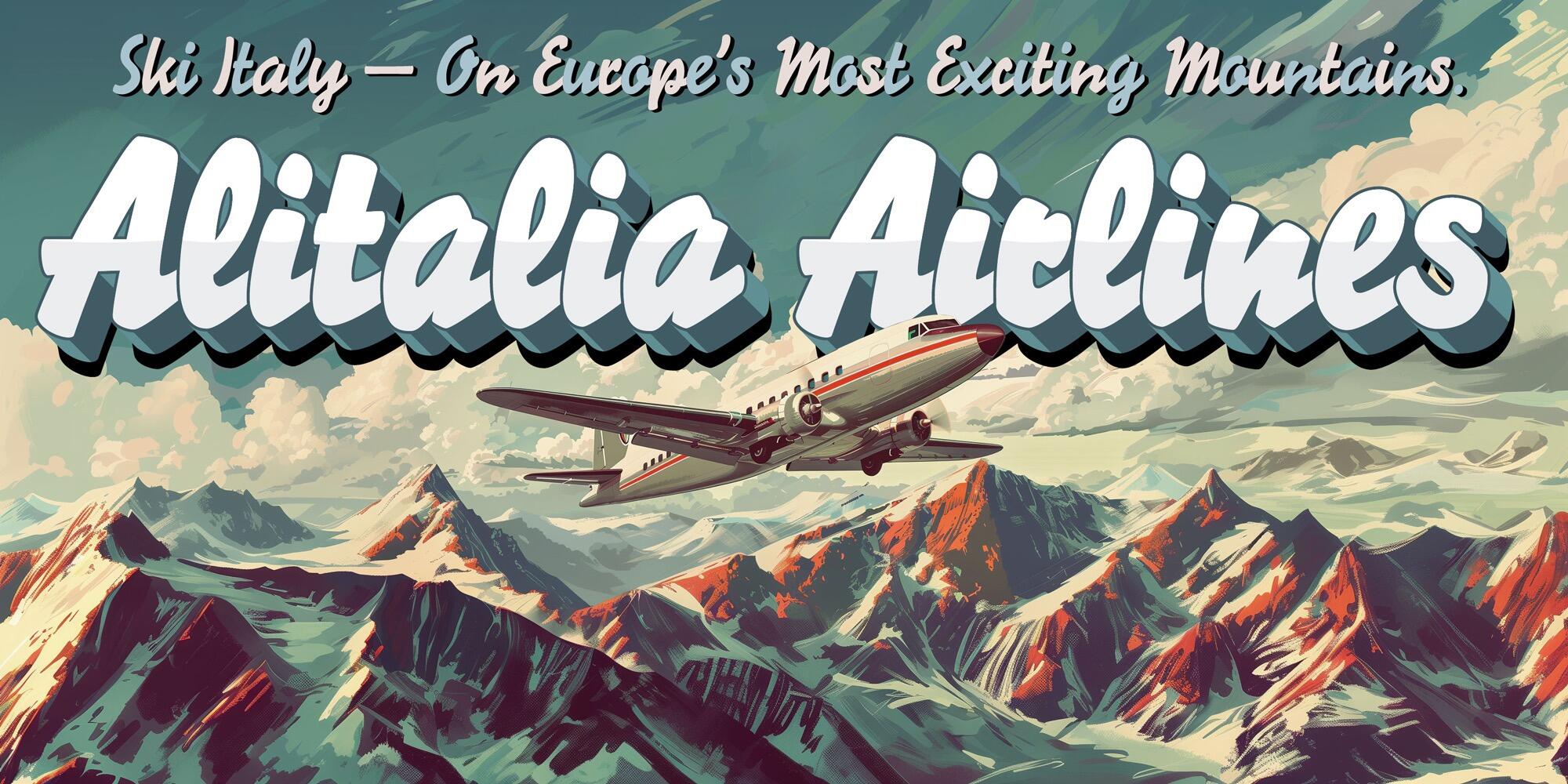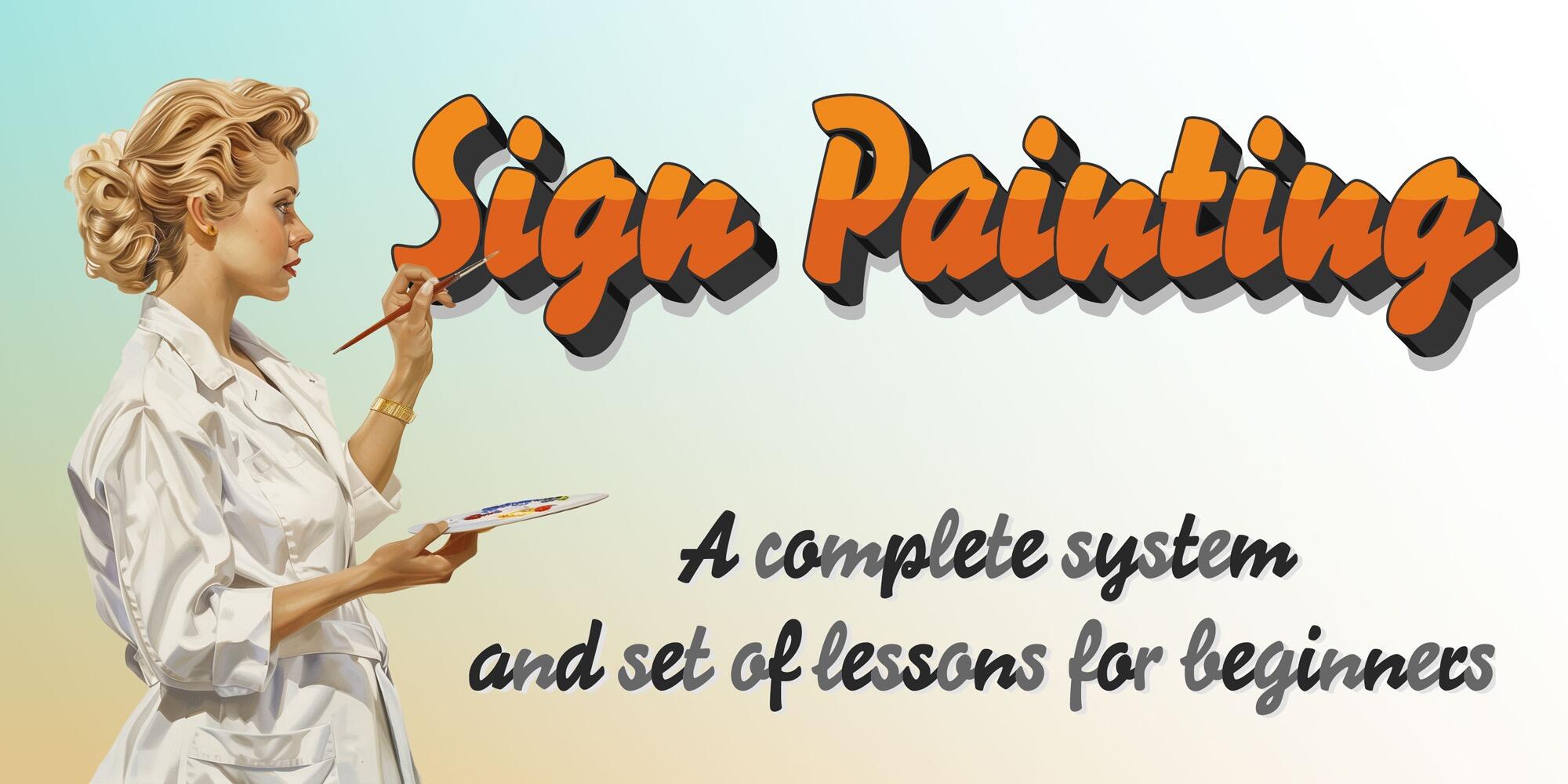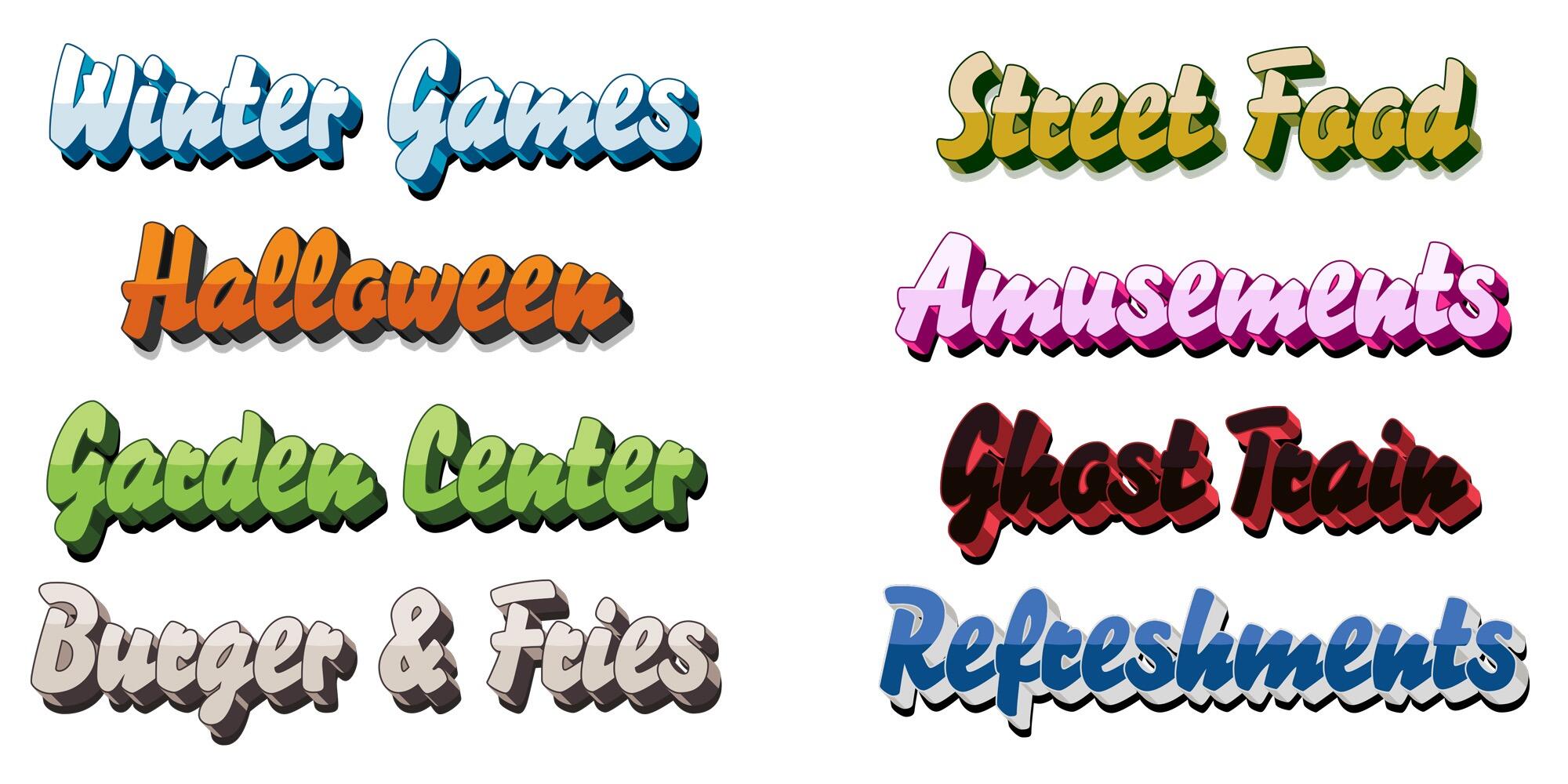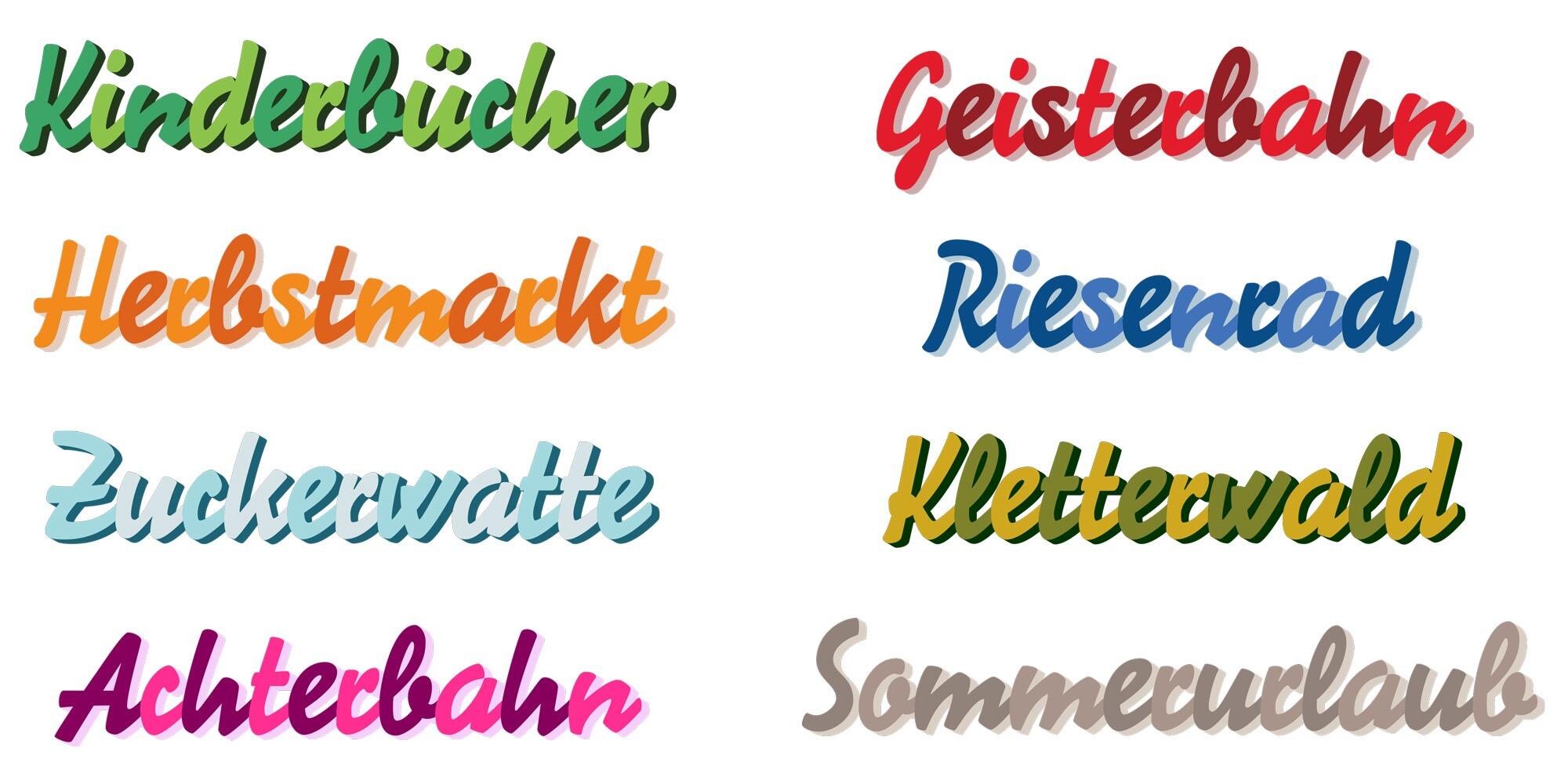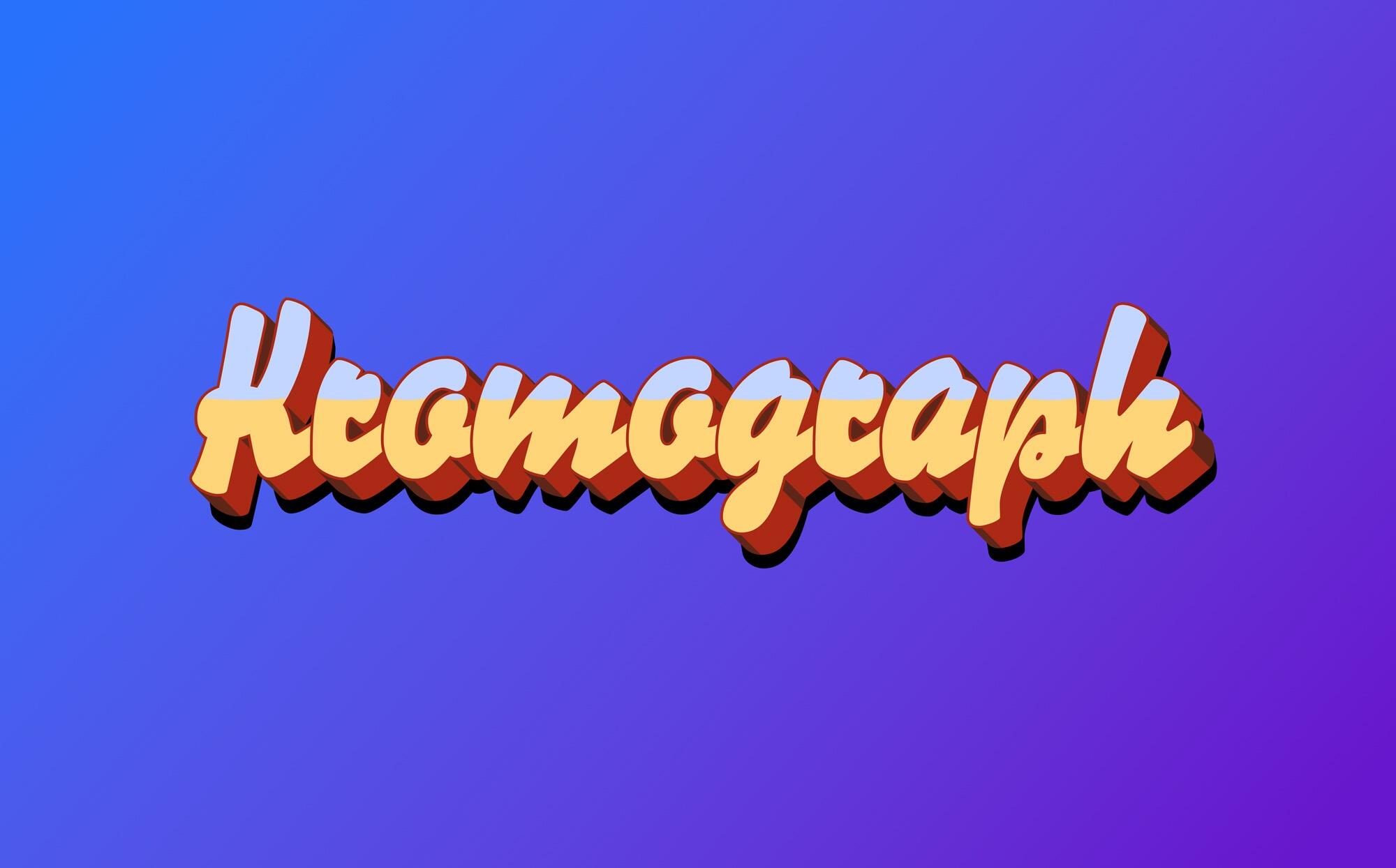
- Antiqua Schreibschrift
Die FDI Kromograph ist eine farbige Schrift auf Basis der Signal-Schriften der H. Berthold AG. Die Schrift ist in zwei Varianten verfügbar: Stil A besitzt einen 3D-Effekt mit fünf Farbebenen. Stil B verfügt über drei Farbebenen und einen automatischen Farbwechsel für aufeinander folgende Buchstaben über das OpenType-Merkmal »kontextbedingte Varianten«.